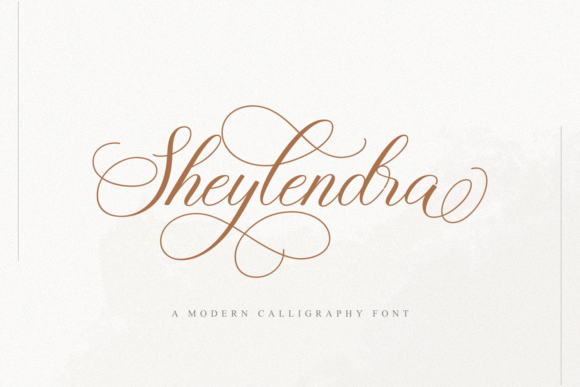
Sheylendra
Sheylendraのような高品質の素材をお探しの場合、このプレミアムパッケージはクリエイティブなプロジェクトに素晴らしい選択です。
POD(オンデマンド印刷)製品、結婚式の招待状、またはソーシャルメディアのグラフィックを作成している場合でも、Sheylendraは理想的です。